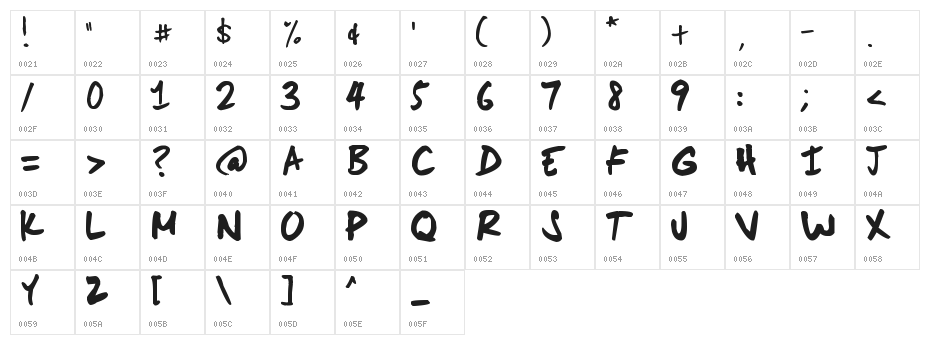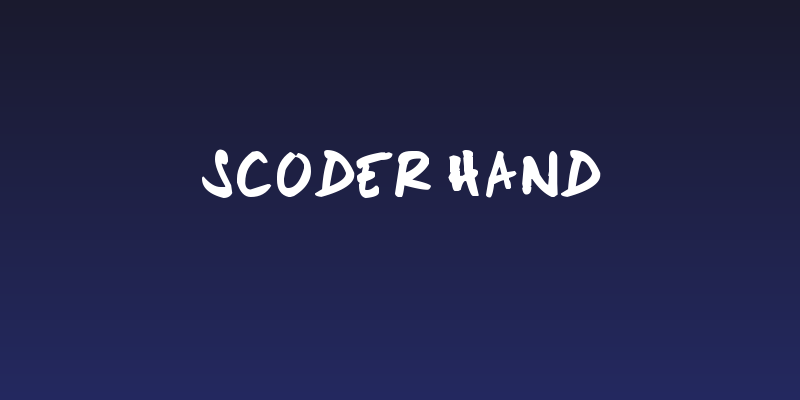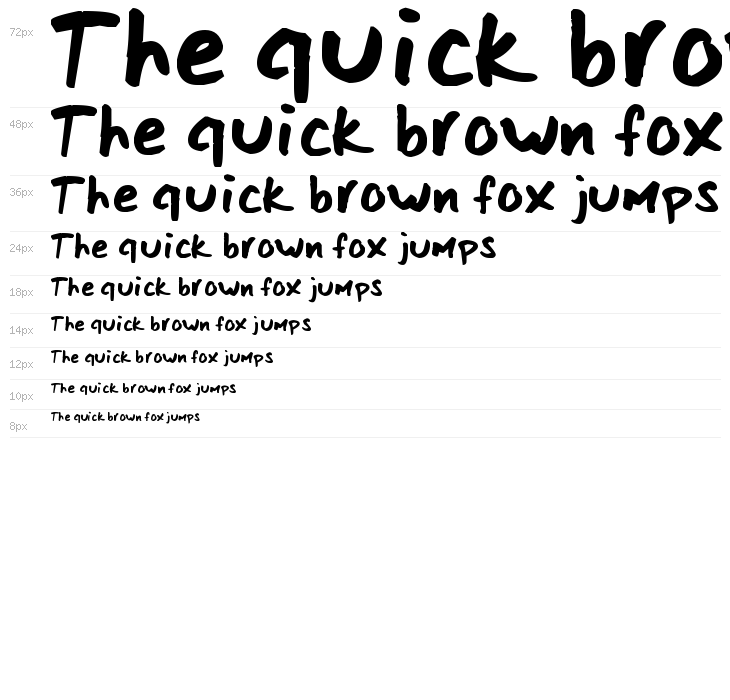
Scoder Hand Font
SCODER-HAND Groß
SCODER-HAND Kleinbuchstaben
SCODER-HAND Anderer Schreiben
| Gesamtstil | Casual, Playful |
| Anwendungsfall | Logos, Headlines, Informal Text |
| Vorgeschlagene Projekte | Ideal for greeting cards, invitations, playful branding, and informal designs. |